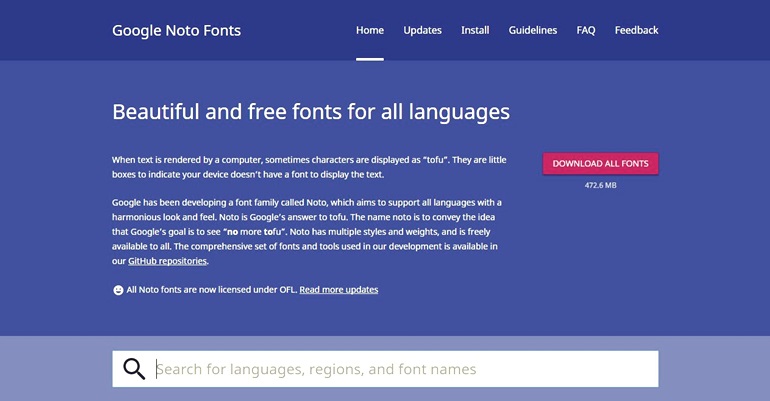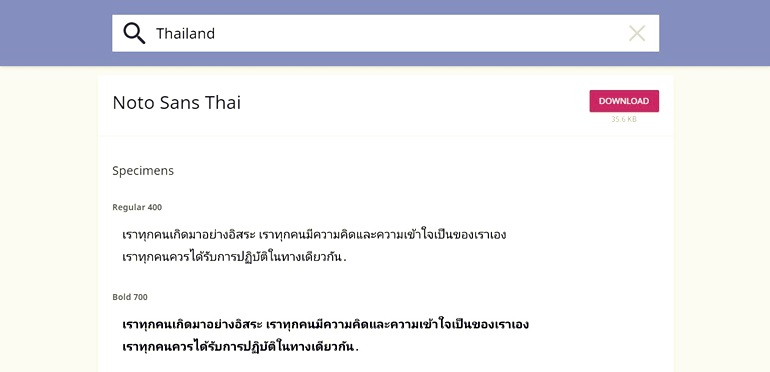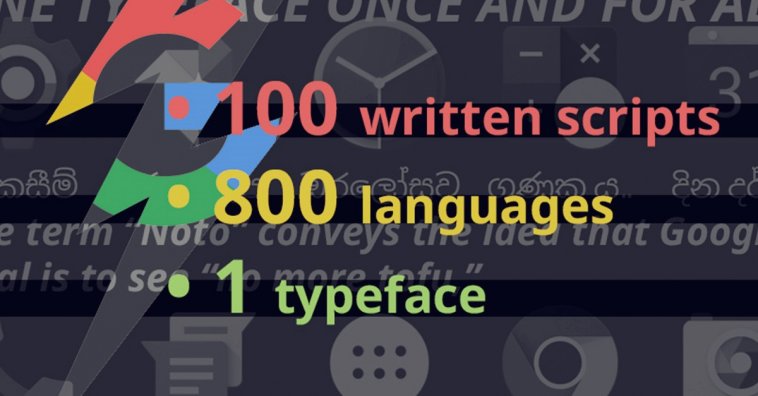
Google ได้เปิดให้ผู้ใช้งานทั่วโลกดาวน์โหลดฟอนต์ “Noto” ได้ไปใช้งานกันฟรี โดยรองรับกว่า 800 ภาษาทั่วโลก ภายใต้ความร่วมมือกับ Monotype และ Adobe ด้วยระยะเวลาพัฒนากว่า 5 ปี มีตัวอักษรให้เลือกถึง 110,000 ตัวอักษร ครบทุกรูปแบบการใช้งานไม่ว่าจะเป็น Thin, Light, DemiLight, Regular, Medium, Bold, และ Black
เอกลักษณ์ของฟอนต์ชุดนี้คือนอกจากจะ “อ่านง่าย” และ “สวยงาม” ยังสามารถแสดงผลได้เกือบทุกภาษาบนโลกใบนี้ จึงเหมาะอย่างยิ่งสำหรับการเอาไปทำเว็บไซต์, แอปพลิเคชัน, หรือสื่อที่ต้องใช้มากกว่า 1 ภาษา เพื่อการแสดงผลที่สมบูรณ์แบบ